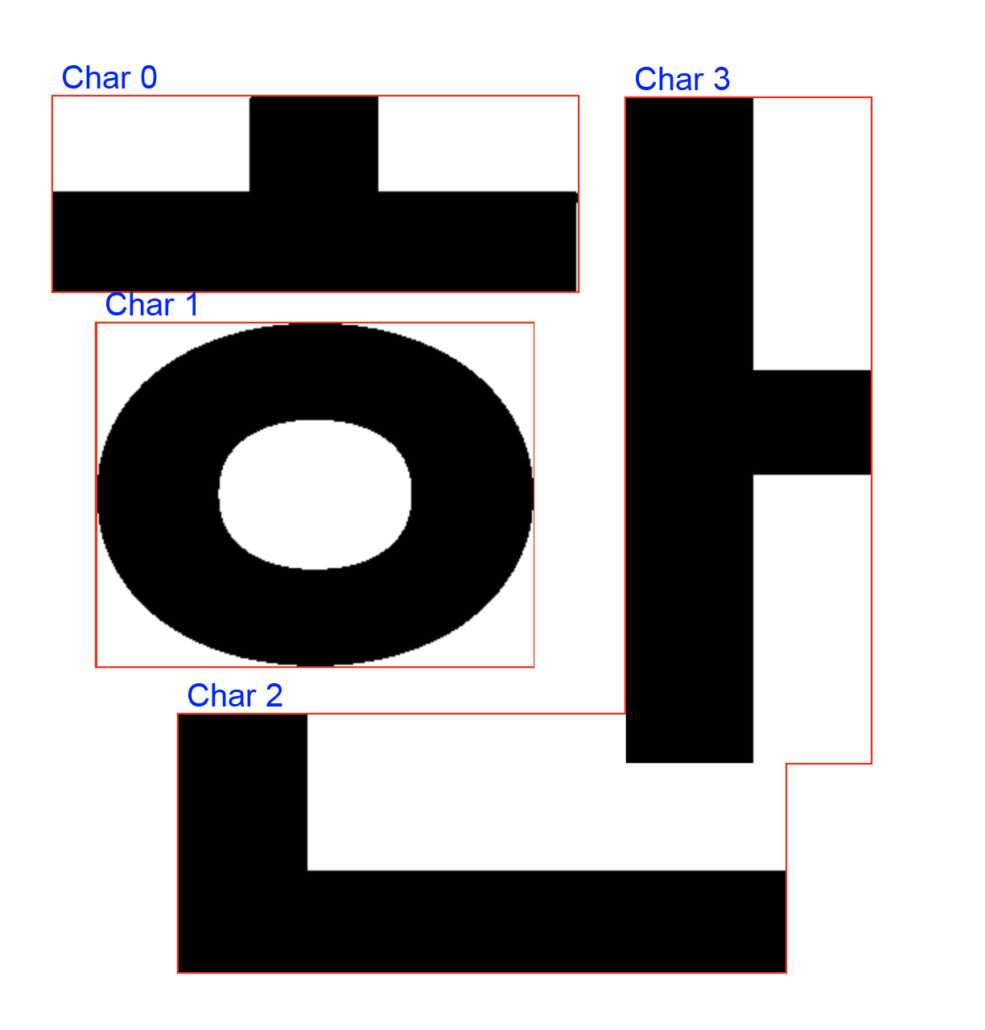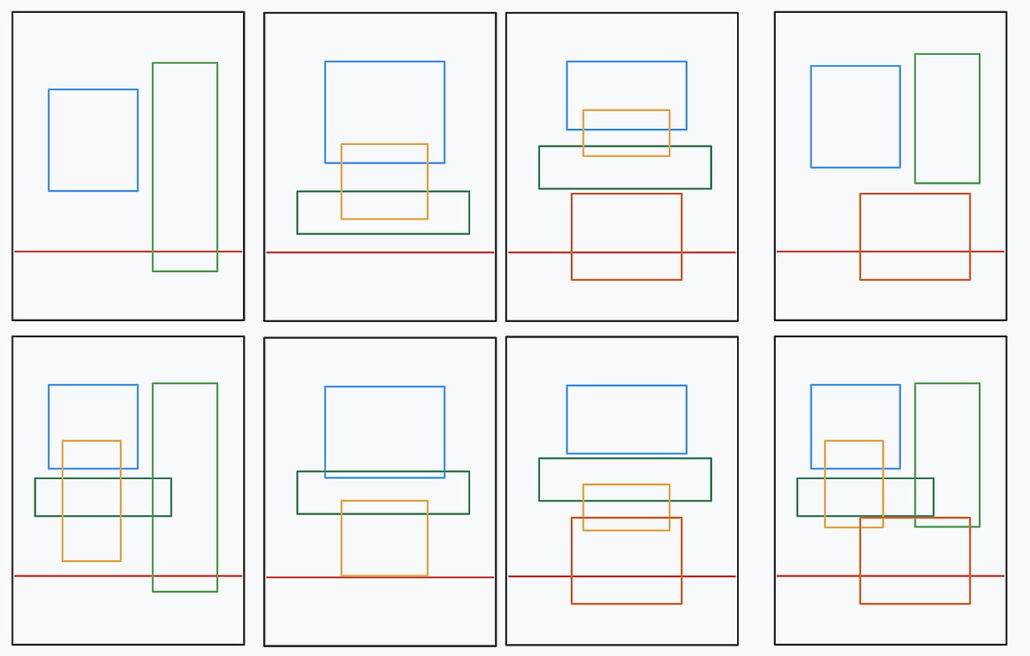
OpenCV, tesseract 등 도입으로 한글폰트 레이아웃 재구성
일단 어떤 폰트건 다시 재구성해서 한글을 구분된 레이아웃으로 분리했습니다. 그리고 글리프별 레이아웃을 기반으로 한 데이터를 재구성할 수 있도록 표준화된 json 파일로 구성하고 svg 로 내보내기 할 수 있게 구성했습니다.
반대로 몇몇 유형의 글자를 쓰면 초성, 중성, 종성을 분리해서 다시 조합하고 특정한 폰트의 레이아웃 정보를 적용하면 새로운 폰트가 생성됩니다.
그동안 손글씨를 특정 패턴에 의해 제작하는 방식을 만들었다면 이번에는 방식으로 폰트제작을 해보려는 중입니다.
글자별로 인식하는게 다르긴한데 그래도 모든 글자를 검토해서 뽑는 것에는 문제가 없습니다. 다만 ㅎ 같은 글자가 2벌로 나눠져서 ㅗ ㅇ 이 부분을 어떻게 처리해야 하나 고민중입니다.
그냥 폰트 만드는데 도움되는 실험이었습니다.